6月29日(水)、「さくらのレンタルサーバ」で株式会社モリサワのWebフォントを無料で利用できる機能がリリースされました!
Webフォントとは
Webフォントとは、サーバー上にフォントを置くことで、ユーザーの環境にないフォントでも表示できるようにする技術のこと。
Webサイトのデザインをする際、サイトの雰囲気を左右するフォントを指定してブラウザで表示させたい場合、Webフォントを導入するケースが多くあります。
しかし、Webフォント導入の際は、導入のための費用が発生したり、クライアントにWebフォントの契約をしていただく必要があるなど面倒な側面もありました。
プラグインで簡単に
これまでも、モリサワのWebフォントサービス「TypeSquare」はレンタルサーバー「ヘテムル」と組み、期間限定でWebフォント利用サービスを展開したことがありました。
しかし、正式なサービスとしてリリースされたのは今回が初めて。
今回スタートしたさくらレンタルサーバのサービスは、当サーバーにインストールしたWordPress上で、TypeSquareのWebフォントの中から厳選された30種類を追加料金無しで利用できるというもの。
サービス開始以降にWordPressをインストールした場合、デフォルトでモリサワのWebフォントを利用できるプラグインが同梱されています。
すでにWordPressをご利用の方は当該プラグインをインストールすれば利用可能です。
このプラグインをインストールすると、プルダウンから選択するだけで、タイトルや本文などの要素別に自由に書体を設定できるほか、記事内容に合わせて一括適用できる「フォントテーマ設定」機能などが簡単に利用できます。
より身近に使いやすく
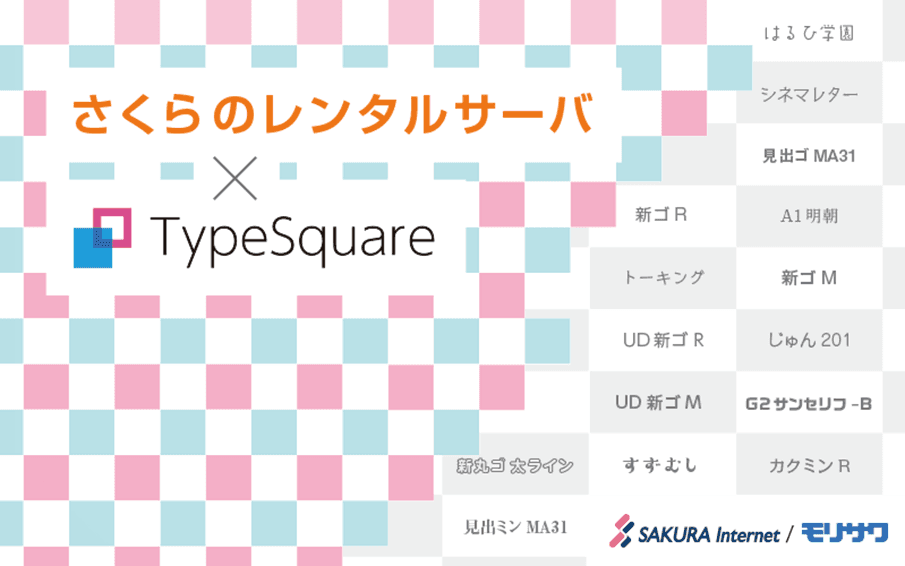
左 リュウミン/ 右 新ゴ 引用元:株式会社モリサワ 公式サイト
今回提供されるWebフォント30種類の中には、リュウミン、新ゴをはじめとする人気書体のほか、「誰にでも読みやすく伝わりやすい」ことをコンセプトに開発されたユニバーサルデザインフォントも含まれています。
今後は、WordPressだけに限らず、静的HTMLへの対応範囲の拡大や、PV数の多い大規模なWebサイトでも利用できるようなプランの拡充も考えているそうです。
Webフォント代がサーバー代に含まれることで企業にかぎらず個人でもWebフォント導入のハードルが下がるほか、新ゴやリュウミンは、雑誌など印刷物を中心に広く利用されている書体なので、紙媒体とWebサイトでブランドイメージの統一がしやすくなるのではないでしょうか。
サーバー側がWebフォントに対応するというのが、これからの新たなスタンダードになりそうですね。